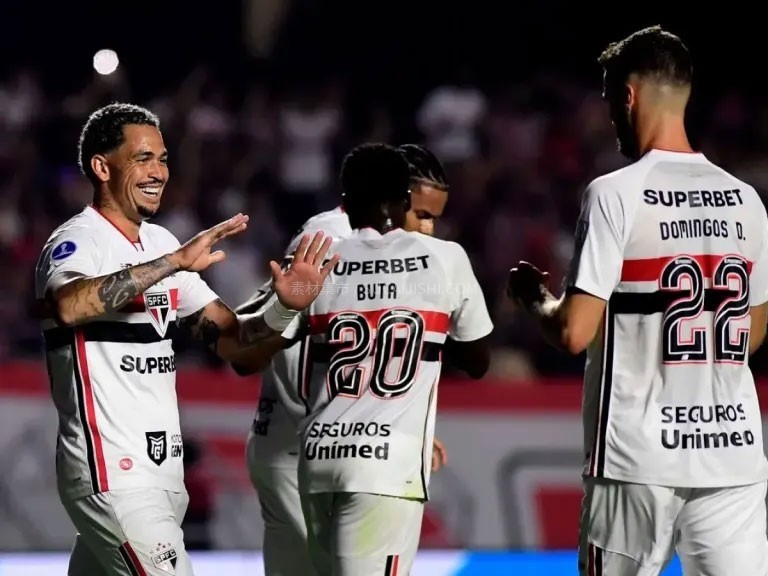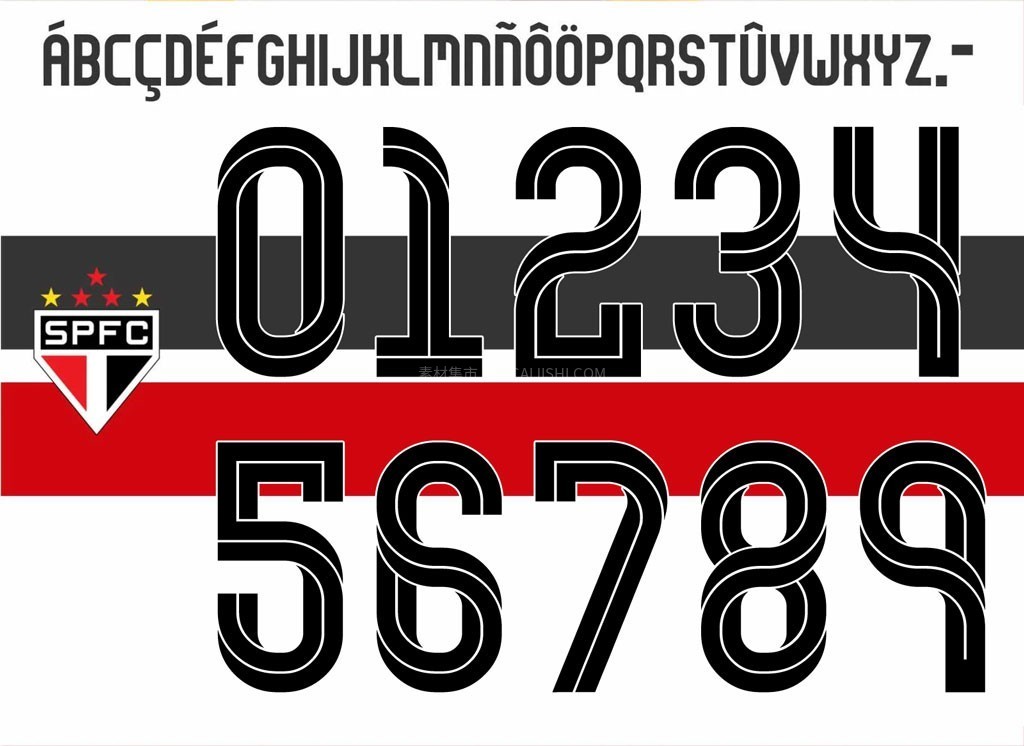
圣保罗足球俱乐部2026赛季球衣字体
圣保罗足球俱乐部2026赛季球衣字体,整体线条平直利落、转角方正,带有微圆角过渡,兼具现代运动科技感与高辨识度。
圣保罗足球俱乐部2026赛季球衣字体
号码细节:立体阴影/双色描边:主场(白色战袍)号码通常采用红色或黑色主体,辅以俱乐部三色(红、白、黑)中的反差点缀边缘。
队徽暗记:号码底部内嵌有单色烫印的圣保罗俱乐部三色菱形盾徽(SPFC crest)。
姓名排版:采用全大写字母(ALL CAPS),字符间距略微收紧,呈微弧形或平直排列于后背号码上方。
圣保罗足球俱乐部2026赛季球衣字体